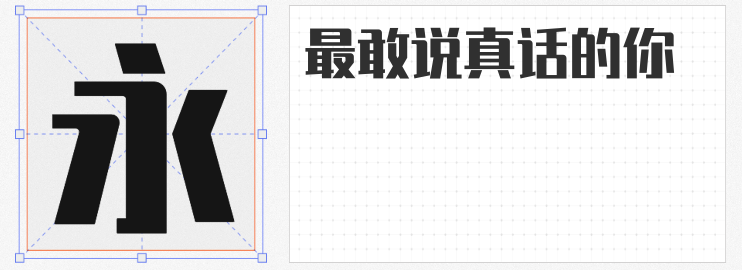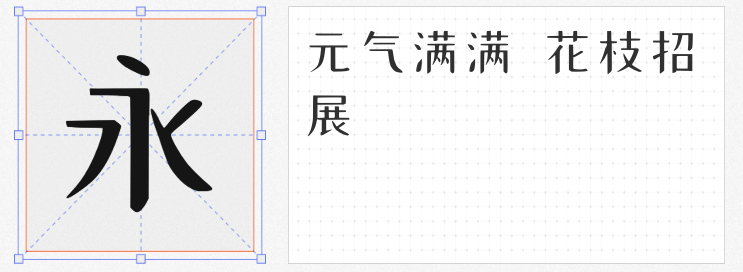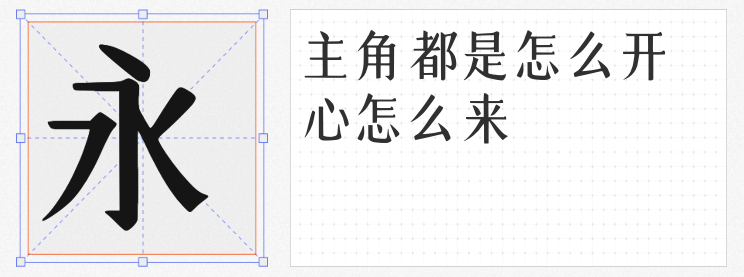
在追求“流量密码”的网感封面设计中,字体是快速传递风格与情绪的关键。既要抓人眼球,又要适配多元主题,更要规避版权风险?以下四款免费商用字体,以鲜明的个性与高适配性,为你的设计注入“网感基因”,轻松打造兼具视觉冲击力与实用性的封面作品。
1. 锐字潮牌真言简2.0免费 特粗
这款字体以“潮牌”为名,笔触浑厚如刀刻,转折处却暗藏柔韧弧度,直角与圆角的碰撞让字形在力量感中透出灵动。特粗的笔画自带“存在感”,无论是科技感、运动风还是复古潮流主题,它都能以端正凝练的姿态成为视觉焦点。推荐用于游戏海报标题、短视频封面大字或品牌slogan设计,瞬间拉满“炸街”气场。
2. 心朵儿体
基于宋体骨架的“心朵儿体”,以稍粗的笔画赋予传统宋体更强的现代感。横细竖粗的经典结构中,融入了圆润的起笔与收笔,让文字既有宋体的端庄,又不失亲和力。适用于美妆、母婴、生活类封面设计,搭配柔和的配色与手绘元素,轻松传递温暖治愈的氛围,是“小清新”风格的绝佳搭档。
3. 平方张亚玲黑方体
这款字体将黑体的稳重与卡通体的俏皮完美融合,笔画粗壮饱满,转折处以圆角弱化锐利感,字形自带“Q弹”属性。其活泼而不失秩序的特质,尤其适合美食探店、综艺娱乐或二次元主题封面。搭配高饱和度色彩与夸张的图形元素,瞬间点燃画面的趣味性,让观众“一眼上头”。
4. 礼品卉自由落体
以“站酷小薇LOGO体”为基底,融合AI生成技术的“自由落体”,笔画如刀锋般锐利,字形紧凑利落,充满几何切割的未来感。其“去装饰化”的设计语言,适配科技、极简、抽象艺术等主题封面,搭配渐变光效或金属质感,轻松营造高级感与先锋性,是追求“高级网感”的设计师必选。
网感封面设计的核心,在于用字体快速传递情绪、建立风格。这四款免费商用字体,或遒劲、或温柔、或趣味、或未来,既能单兵作战撑起封面“C位”,也能灵活组合碰撞出多元火花。无需为版权担忧,尽情释放创意,让你的封面设计在信息流中“脱颖而出”!